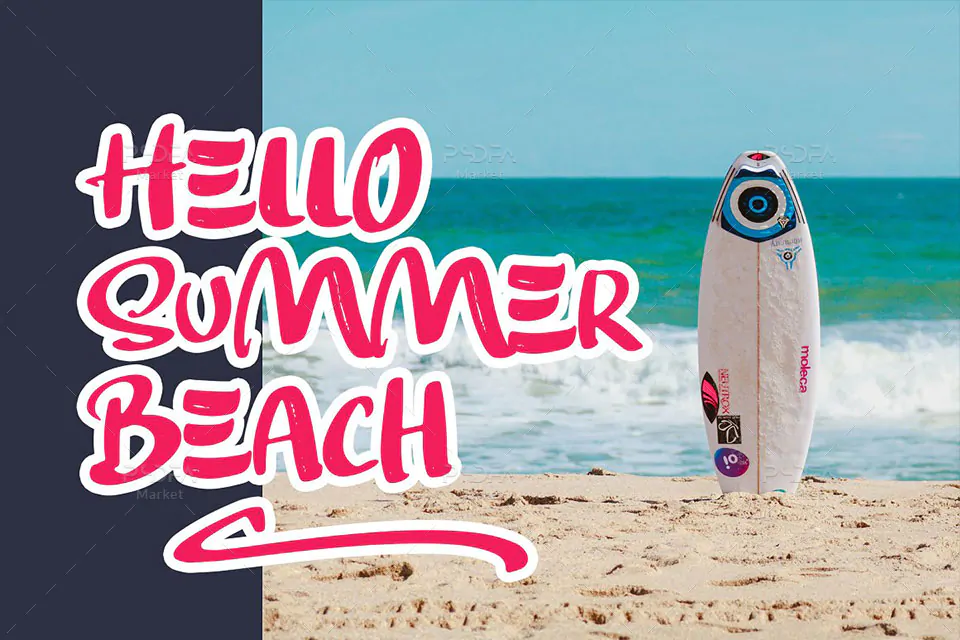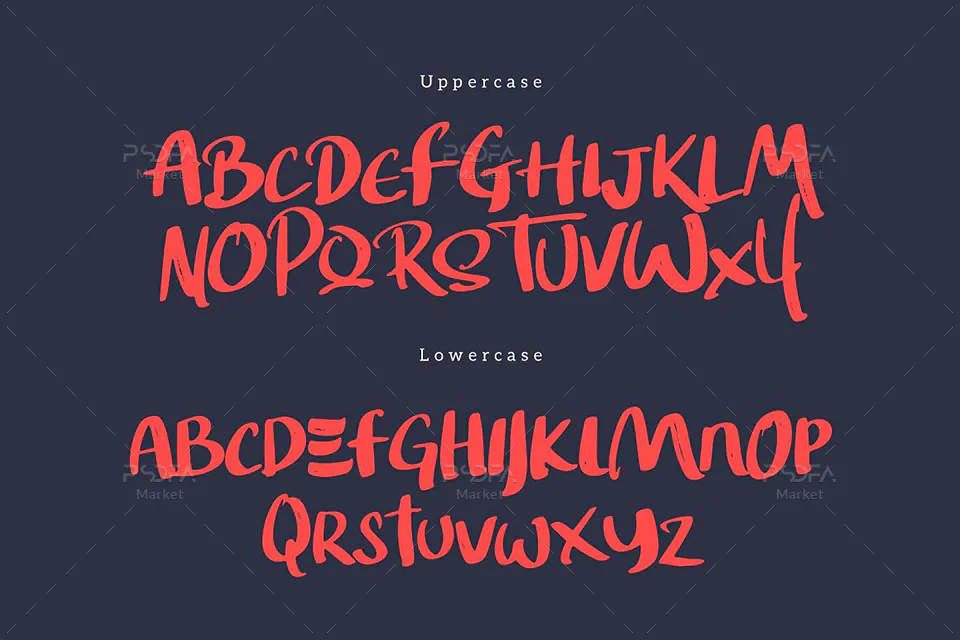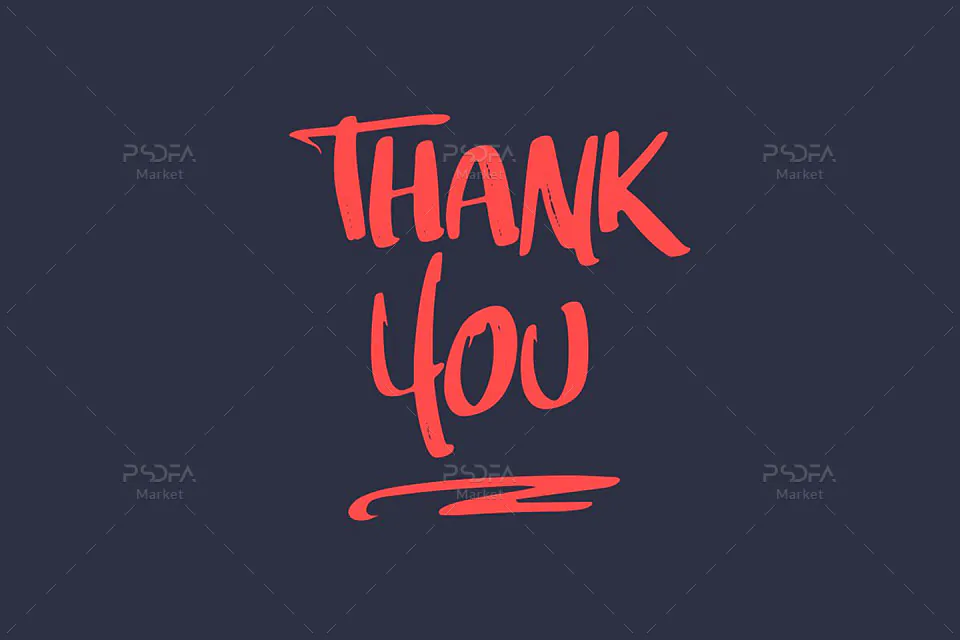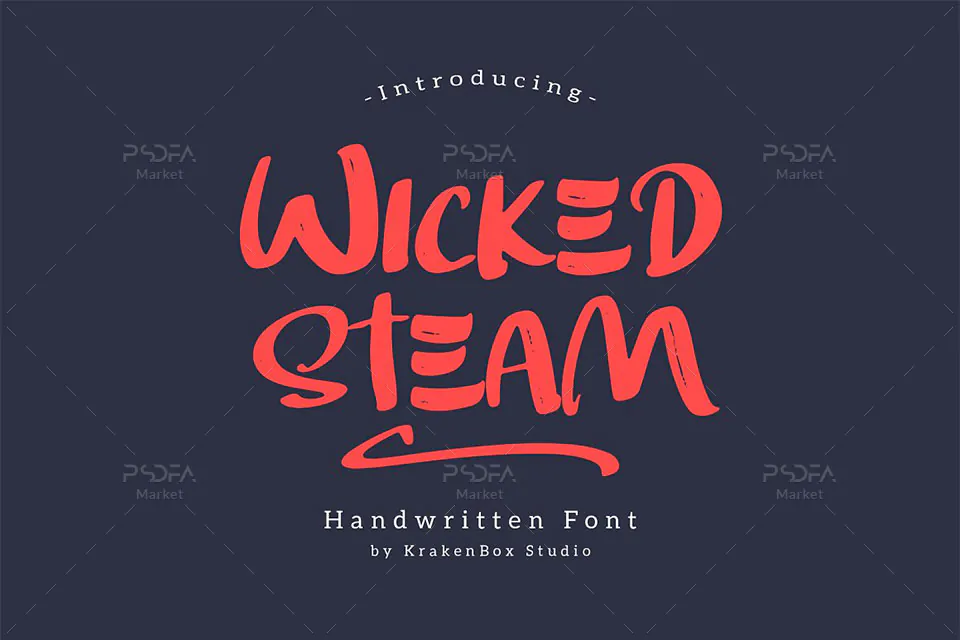
فونت دستنویس بولد و ضخیم انگلیسی Wicked Steam Handwritten Font یک قلم شیک و زیبا است که مناسب جهت استفاده در طرح و پروژههای گرافیکی مختلف از جمله طراحی انواع پوستر میباشد. این فونت زیبا در قالب فایلهای OTF, TTF, WOFF بر روی سایت قرار گرفته است که با نصب یکی از این دو فرمت otf یا ttf در پوشه فونتهای سیستم قادر به استفاده از آن در تمام نرم افزارهای گرافیکی و ویرایشگر متن از جمله نرم افزار محبوب فتوشاپ، ایلاستریتور، مجموعه نرمافزار آفیس همچون ورد و پاورپوینت و … خواهید بود.
فونت Wicked Steam در وزن معمولی (Regular) طراحی شده است که میتوانید از آن در طراحی انواع کارت تبریک، کارت پستال، کارت ویزیت، کاور آلبوم موزیک، طراحی انواع بنر، پوستر، تراکت، تقویم، بروشور و دیگر طرحهای گرافیکی استفاده کنید. از نسخه وب این فونت نیز میتوانید در طراحی صفحات وبسایت استفاده نمائید. همچنین یک فونت دیگر شامل کاراکترهای کشیده نیز در فایل محصول قرار دارد که از آن میتوان در تزئین و زیبا سازی طرح و تصاویر بهره برد.
- کیفیت بالای قلم
- نام فونت: Wicked Steam
- وزن: Regular